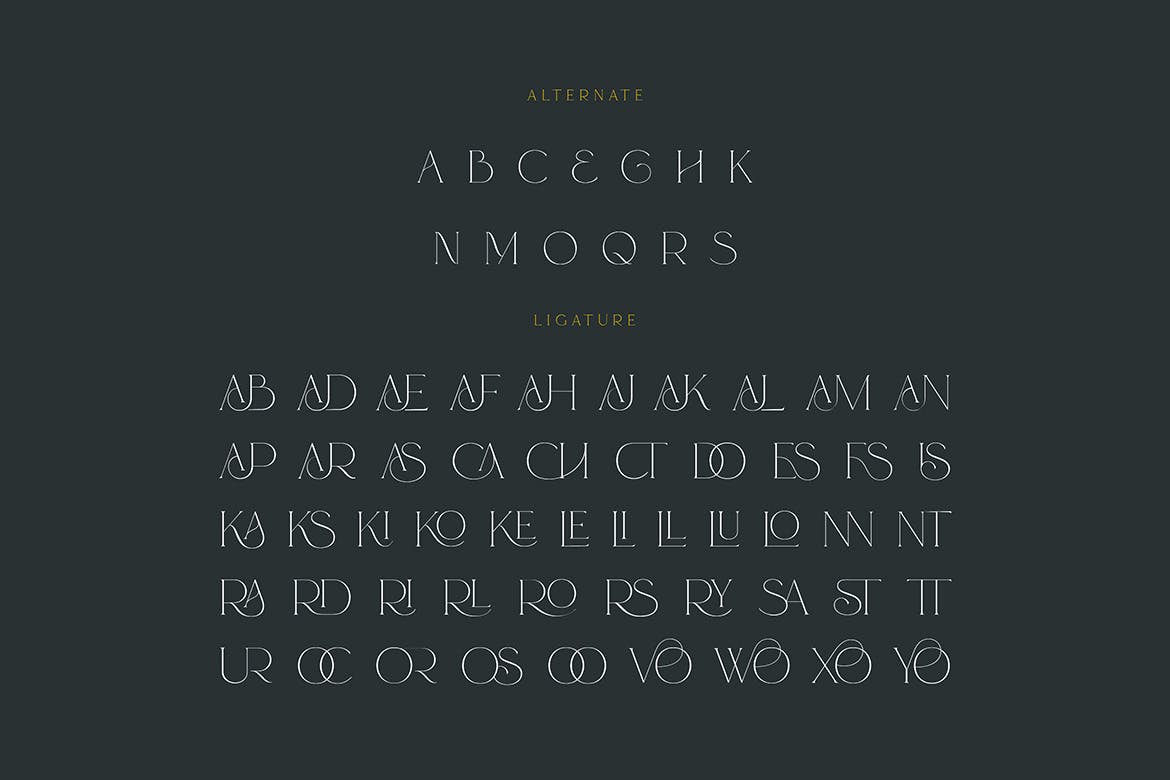
Risuali Luxury Typeface
فونت لوکس و مدرن Risuali با طراحی زیبا و منحصر به فرد مناسب برای پروژه‌های شما.
فونت Risuali یک فونت سریف مدرن، شیک و لوکس است که برای پروژه‌های خاص شما طراحی شده است. این فونت با سبک هنری و رمانتیک خود، گزینه‌ای عالی برای هر پروژه برندسازی به شمار می‌آید. با وجود تعداد زیادی از کاراکترهای جایگزین و لیگاتورها، شما می‌توانید طراحی لوگو یا هدر وب‌سایت منحصر به فرد و اصیلی ایجاد کنید!
• پشتیبانی از چند زبان
• تعداد زیادی کاراکتر جایگزین
• تعداد زیادی لیگاتور
• عالی برای پروژه‌های برندسازی مدرن!